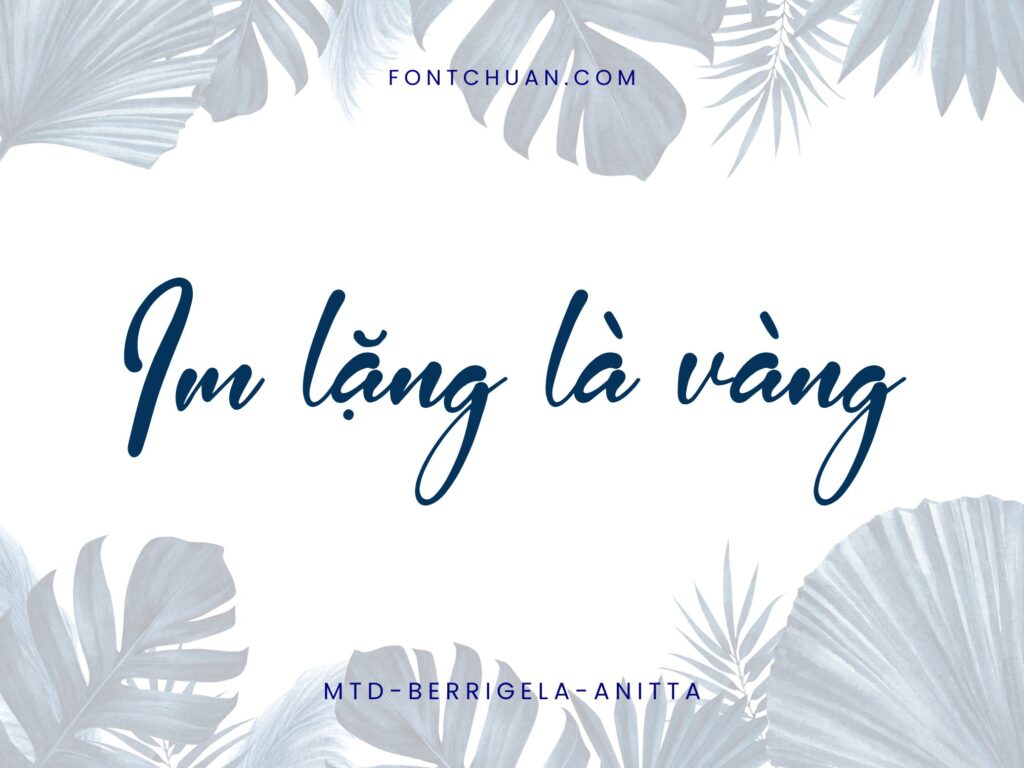
Font MTD Berrigela Anitta Việt Hóa
Berrigela Anitta là một font chữ mang phong cách viết tay hiện đại, nổi bật với các đường nét mềm mại và thanh lịch. Với thiết kế nhẹ nhàng nhưng vẫn mang đến sự tinh tế, font này rất phù hợp để tạo điểm nhấn cho các dự án sáng tạo. Để hỗ trợ cộng đồng thiết kế Việt Nam, Mộc Hạ đã Việt hóa font Berrigela Anitta, giúp font này hỗ trợ đầy đủ tiếng Việt cùng hơn 200 ngôn ngữ khác. Phiên bản Berrigela Anitta Việt hóa đã được thành viên Font Chuẩn sưu tầm và đăng tải nhằm mang đến sự lựa chọn phong phú hơn cho các nhà thiết kế.
Về đặc điểm thiết kế, Berrigela Anitta có các ký tự uốn lượn nhẹ nhàng, tạo cảm giác tự nhiên và bay bổng. Font này có độ tương phản nhẹ, giúp đảm bảo tính dễ đọc mà vẫn giữ được vẻ thẩm mỹ. Berrigela Anitta đặc biệt phù hợp với các thiết kế thiệp cưới, logo thương hiệu, typography nghệ thuật và các sản phẩm liên quan đến thời trang. Ngoài ra, font này cũng rất thích hợp cho các ngành nghề như quảng cáo, ẩm thực và giáo dục, mang lại phong cách chuyên nghiệp và tinh tế. Berrigela Anitta cũng là lựa chọn lý tưởng cho các sự kiện như Valentine, Sinh nhật và các lễ hội.